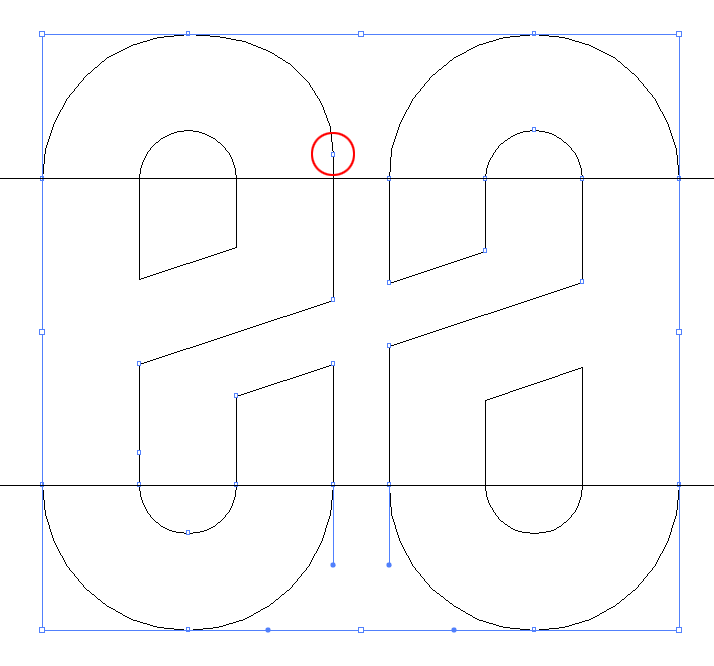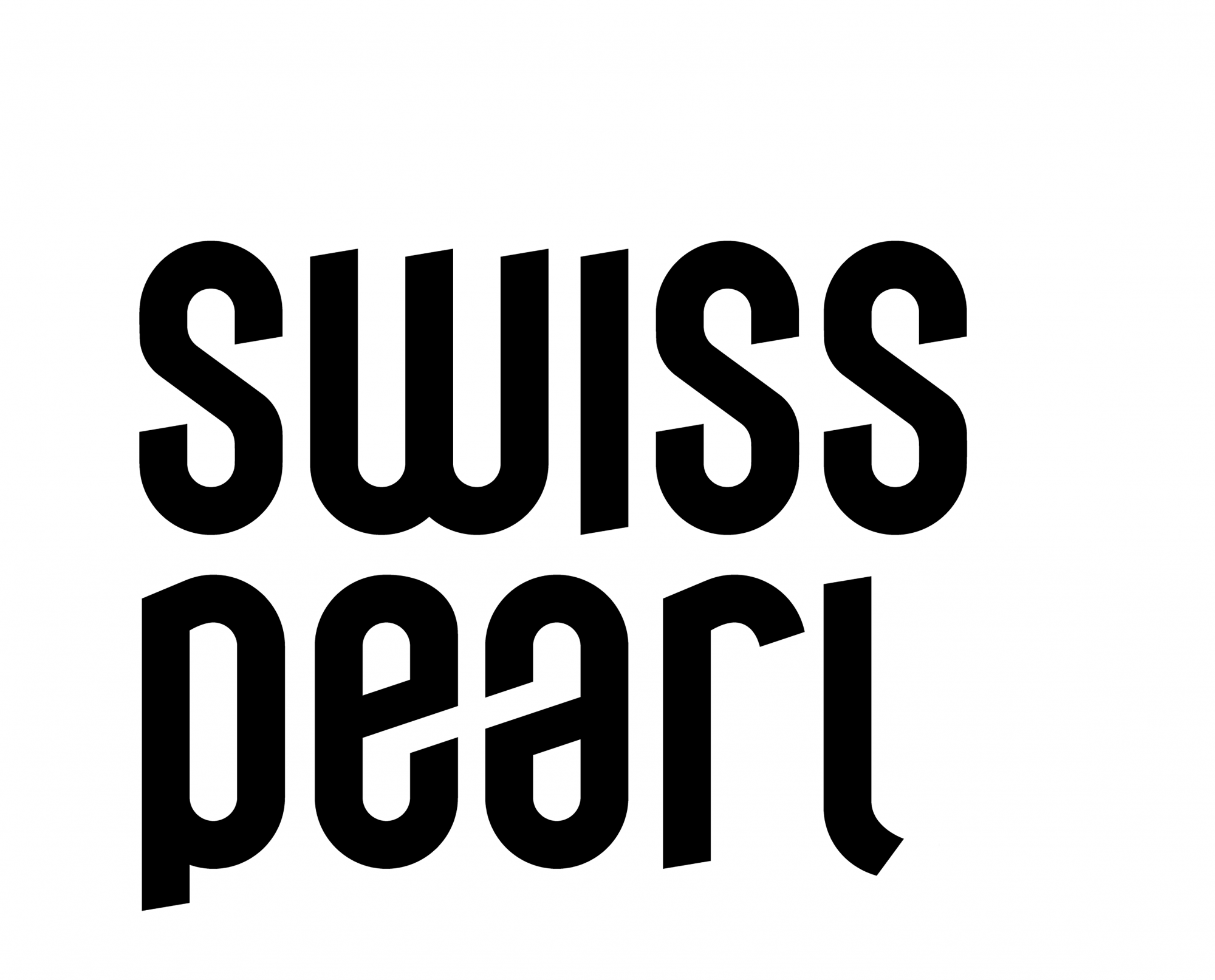
Schriftsuche für Logo swisspearl & eternit
Ich bin auf der Suche nach der Schriftart, die neu für das Logo von Swisspearl und Eternit verwendet wurde.
Besonders markant sind das a & e mit den schräg verlaufenden Diagonalen.
Sedus Stoll verwendet eine ähnliche Schrift und ich hatte vermutete, dass sie vielleicht für das Logo angepasst wurde?
Das ist sehr wahrscheinlich aus keiner Satzschrift erstellt. e und a sind quasi deckungsgleich, die Schräge wurde aber so angepasst, dass das Kreuz entsteht.
Dass dem Reinzeichner (m/w/d) dabei ein Fehler unterlaufen ist und er/sie/es dabei einen Ankerpunkt versehentlich verschoben hat, wie man auch schon am Bauch des e rechts oben erkennen kann, ist ein weiteres Indiz für "handmade".